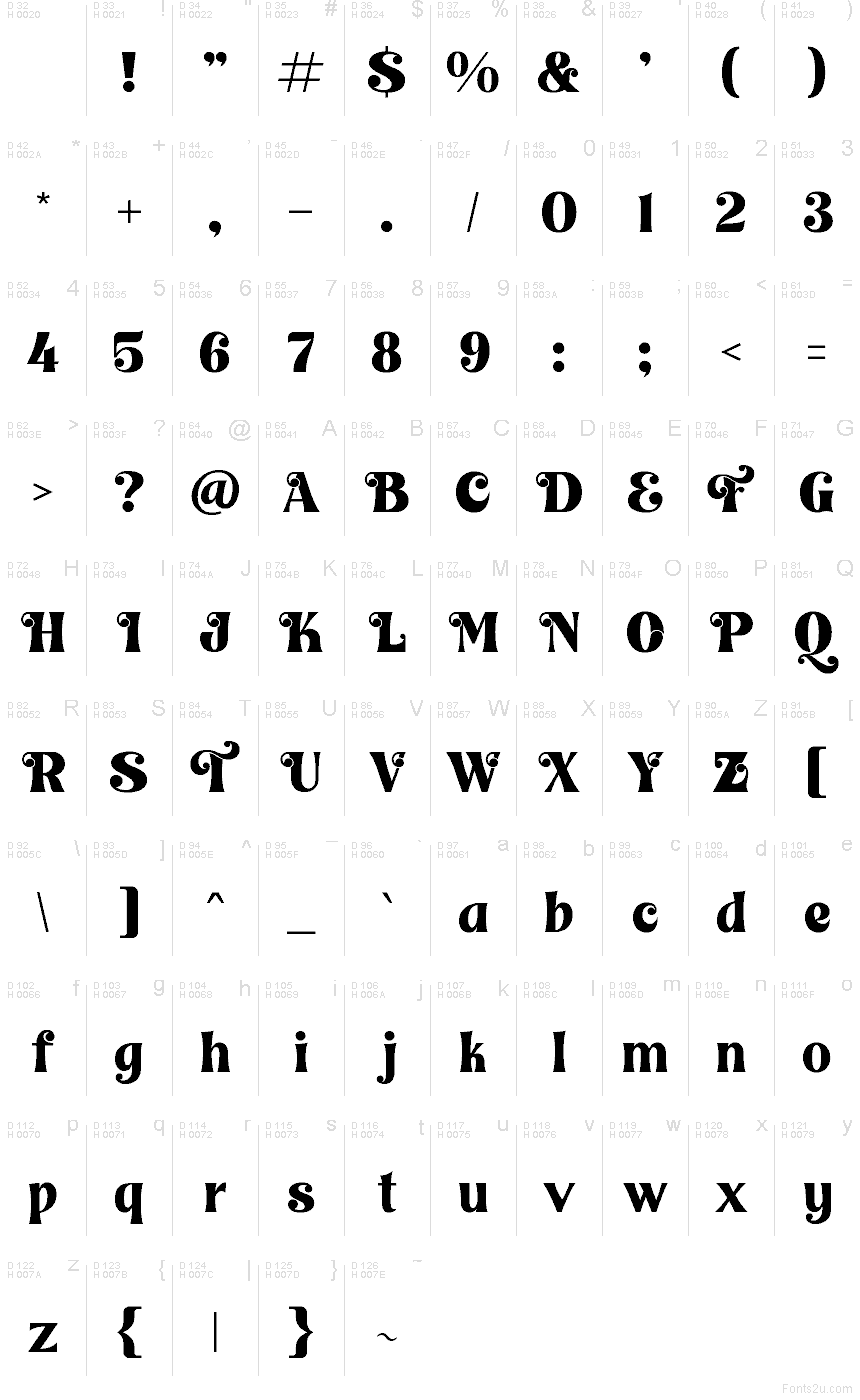
Bright Kenly od TimelessType je bezplatné retro display písmo s veselým, pohádkovým nádechem. Písmena kombinují měkké, baculaté křivky s ostrými zakončeními, což dává písmu živý rytmus, který působí vintage dojmem, aniž by byl zbytečně zdobný.
Skvěle se hodí pro branding kaváren, hravé obaly, butikové plakáty, přáníčka a titulky, kde krátký text potřebuje dodat teplo a dynamiku. Jako bezplatné písmo je Bright Kenly ideální také pro náhledy titulů, skici log a monogramy, protože zaoblené tvary a kudrnaté detaily dodávají výrazný charakter i pár písmenům.